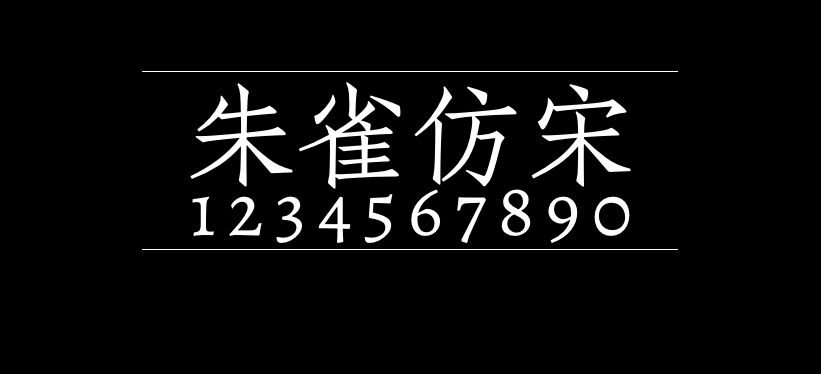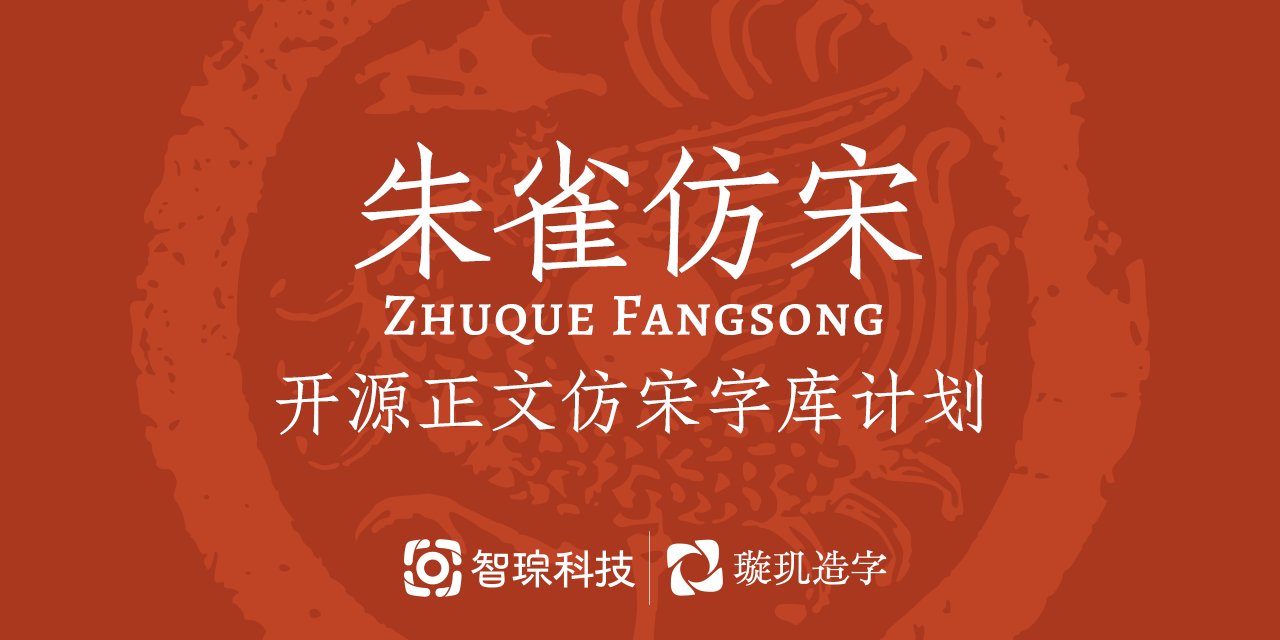
朱雀仿宋
「朱雀仿宋」是璇玑造字的开源仿宋字体计划,志在最终提供高质量的、支持多语言的正文仿宋解决方案,朱雀仿宋基于OFL开放字体协议发布,您可以免费用于个人和商业用途;目前该字体已覆盖GB2312标准的6763字的93%,常用字基本都不缺,您可以放心下载使用。
仿宋作为「宋黑仿楷」中文四大基础字体之一,长期缺乏开源许可证下的选择。我们希望「朱雀仿宋」可以弥补这一空缺,为开源软件与 TeX 社区贡献一份力。
上世纪初,仿宋活字一度品类繁盛,开发、应用风行一时。然而时过境迁,市面上的仿宋最终收敛于「华丰真宋」一系,这也是今天大多数人所熟悉的仿宋样貌。「朱雀仿宋」则以民国仿宋活字「南宋」为蓝本,在满足现代排印需求的前提下,尝试为正文仿宋字库带来一缕新鲜空气。
当前我们发布的「朱雀仿宋」仍为「预览测试版」,尚处于项目早期阶段;无论是设计风格还是字形、排版质量,都不代表正式版情况。因此,
「朱雀」的未来,由你定义
璇玑正在尝试一种全新中文字库设计模式。得益于我们开发的最新技术,璇玑的设计师可以直接将人工智能作为设计工具去使用,我们也因此能以迭代的方式开发「朱雀」。
设计故事
开发一套开源仿宋字库的想法最早始于 2021 年初,是继「未来荧黑」项目之后,我们认为更有意义、也更具难度的挑战。随着设计研究的深入与技术进步,特别是去年以来 AIGC 技术的爆发,实现这一想法在今日遂成可能。
朱雀仿宋
《足本欧阳永叔全集》,1936 年大东书局刊行。使用南宋活字排印,主创自藏。
「朱雀仿宋」改刻自民国活字「南宋」,试图为这套沉睡数十年的字体赋予新生。「南宋」于 1932 年由「百宋书局」推出,韩佑之设计原稿,邹根培雕刻字模。一经面世,即广泛用于书籍、期刊排印。「南宋」与大多数正文字体的设定不同,重心略靠右下;结构中宫收紧、撇捺舒展,笔画的粗细变化强烈;含蓄秀美而充满力量感,在排印标题和正文时展现出浓厚的「书卷气」。
在「南宋」活字的基础上,「朱雀仿宋」稍稍削弱了笔画的对比度,适当地规整了字形结构与版面效果,同时最大程度地保留了「南宋」的独特气质与活字趣味。
「朱雀」是中国传统文化中「四象」之一,南方七宿之神。「朱雀」之名,与「南宋」渊源以及「璇玑造字」的品牌名相合。
朱雀的西文与符号暂采用 Alegreya 的一个外插值实例。Alegreya 由 Huerta Tipográfica 的 Juan Pablo del Peral 创作,同样以 SIL Open Font License 1.1 发布。